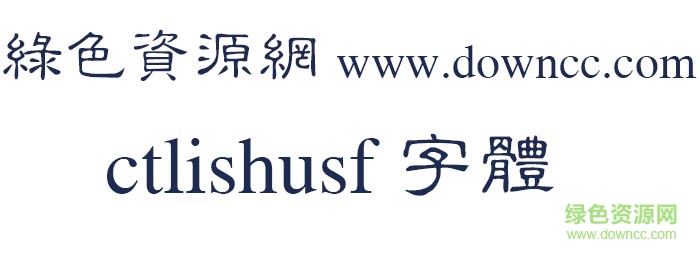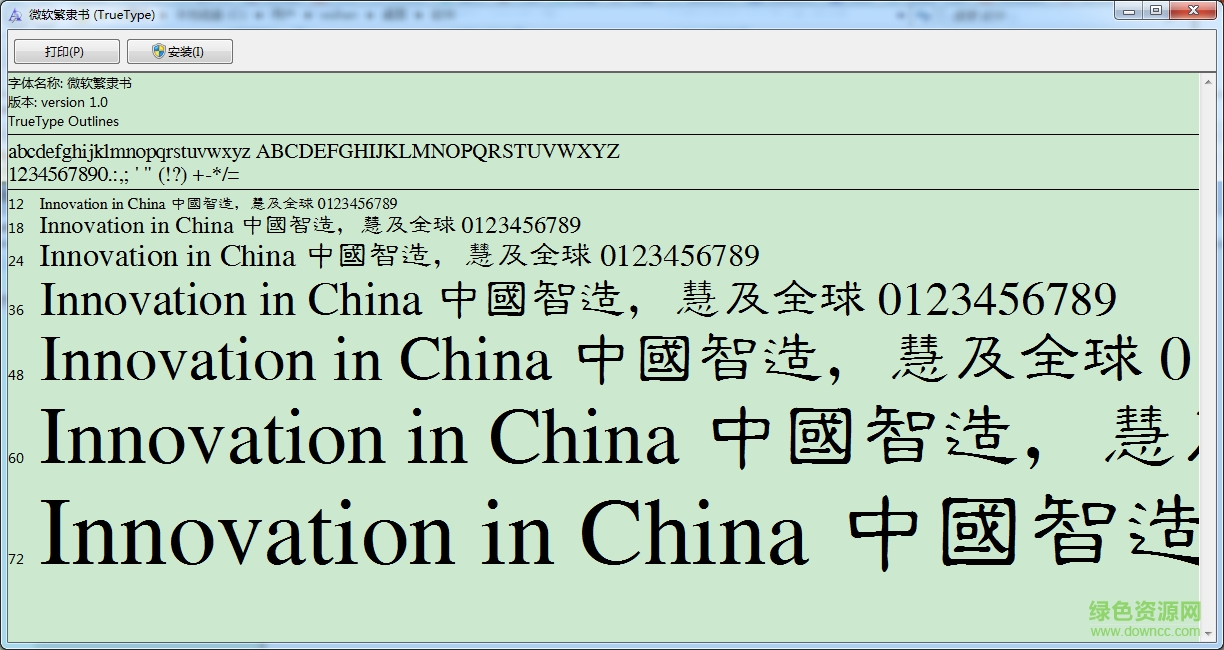
ctlishusf字體是一款很有個性的繁體隸書字體,這款字體雖為繁體字,但是實(shí)用性還是很強(qiáng)的,可以用于很多方面,小編知道有很多朋友在找這款字體,因此已經(jīng)將這款字體打包好了,歡迎大家來綠色資源網(wǎng)下載。
ctlishusf是一款應(yīng)用范圍非常廣泛的繁體隸書字體,此款字體字型飄逸,具有行云流水、酣暢淋漓等特點(diǎn),擁有完整的字庫,支持中文、英文、數(shù)字輸入,喜歡的朋友歡迎來綠色資源網(wǎng)下載!